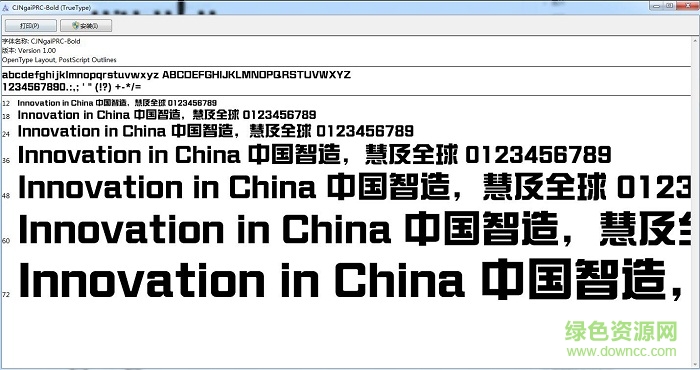
cjngaiprc bold
cjngaiprc bold是什么字體?cjngaiprc bold是一款粗體的綜藝字體,線條粗壯,結(jié)構(gòu)勻稱,便于閱讀和識別,用在平面設(shè)計中能夠給人以清晰的視覺印象,有需要者快來綠色資源網(wǎng)下載吧!
cjngaiprc bold